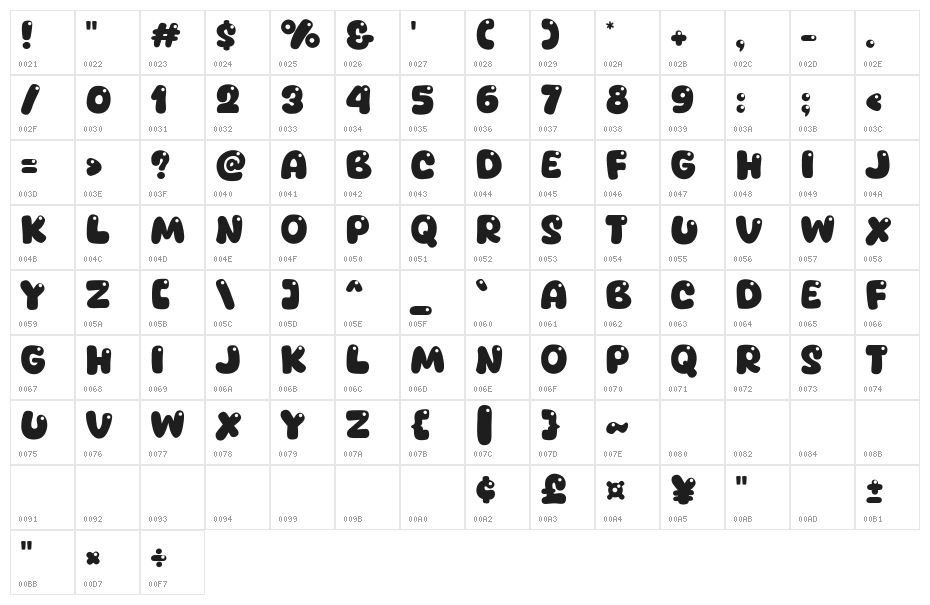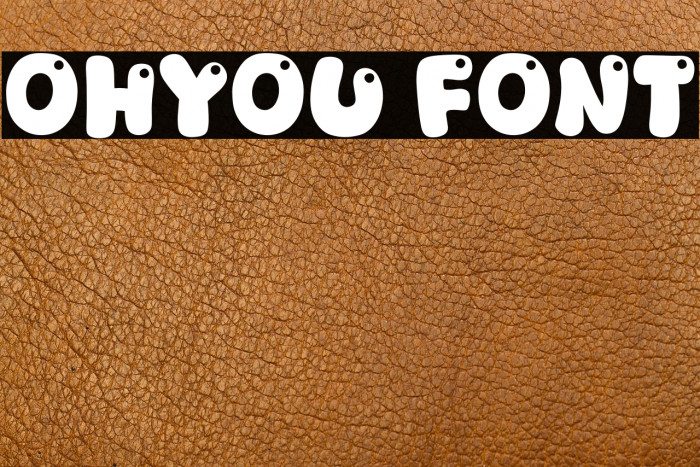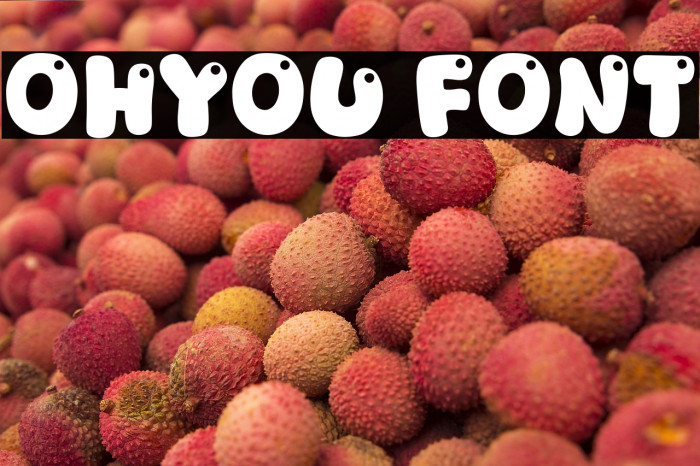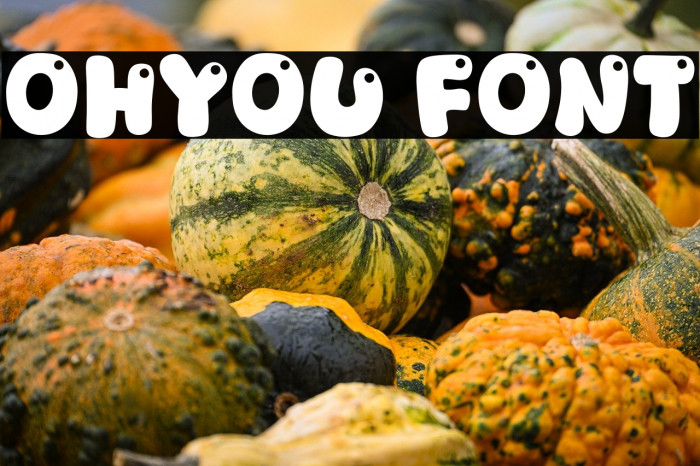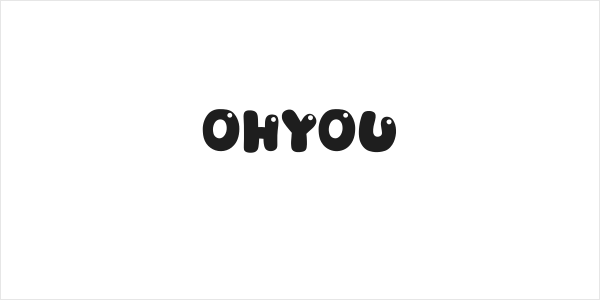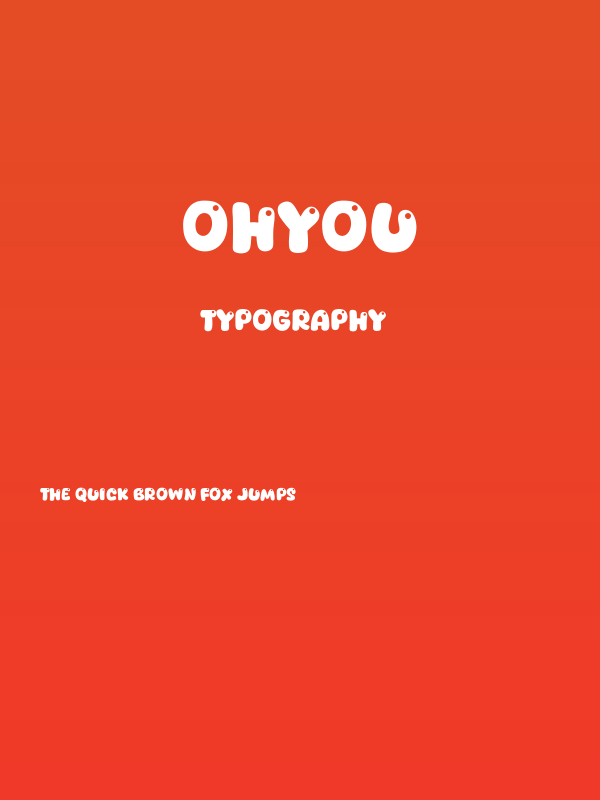
Ohyou Font
| Gesamtstil | Playful, Whimsical |
| Vorgeschlagene Projekte | Ideal for children's books, playful branding, party invitations, and creative posters. |